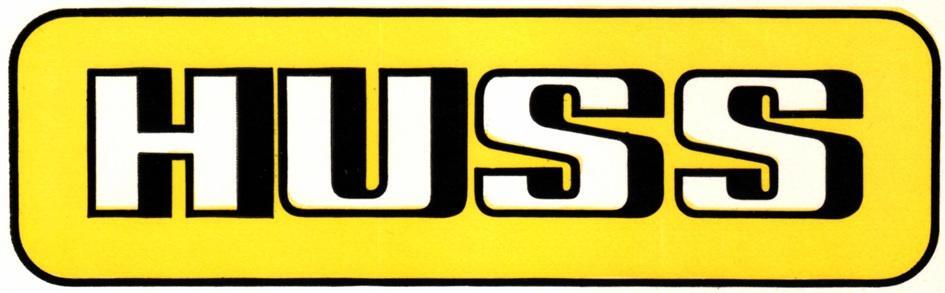
Ist HUSS Maschinenfabrik aus Bremen handgemacht oder doch eine Typo?
Ich habe bereits alle Fontidentifizierungs-Maschinen durchrattern lassen und bin bis hier hin nun ohne weitere Anhaltspunkte gekommen. Habt ihr als Community ggf. noch Ideen, welche Schriftart -die vielleicht angepasst wurde- es sein könnte oder aber bestätigt mich, dass es ein gänzlich handgemachter Schriftzug ist?
Genau: Die HUSS gab es bereits seit 1919 mit der Anfertigung von Schiffsteilen. Soweit mir bekannt, ging es unter diesem Schriftzug ab 1969 los und HUSS entwickelte die ersten Fahrgeschäfte für die Reise.